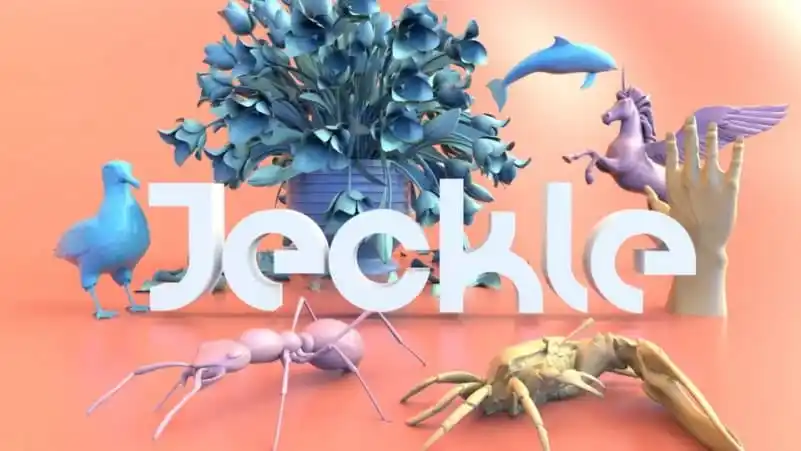
A Jeckle Display Font é uma escolha perfeita para quem busca personalidade moderna em um ambiente minimalista. Especialmente adequada para logotipos em maiúsculas, sua geometria elegante e serifless oferecem uma aparência clara e potente. Ela se destaca por ser livre e geometricamente geométrica, tornando-se perfeita para textos curtos e headlines, bem como para gráficos de marca e identidade visual. Com um design cuidadoso realizado pelo designer Jorge Villareal na plataforma 99designs, essa fonte moderna é uma ótima opção para quem busca elementos únicos e coerentes em seu projeto visual. Sua simplicidade e eficiência fazem dela uma escolha agradável tanto para designers quanto para empresas que desejam criar um design limpo e forte.